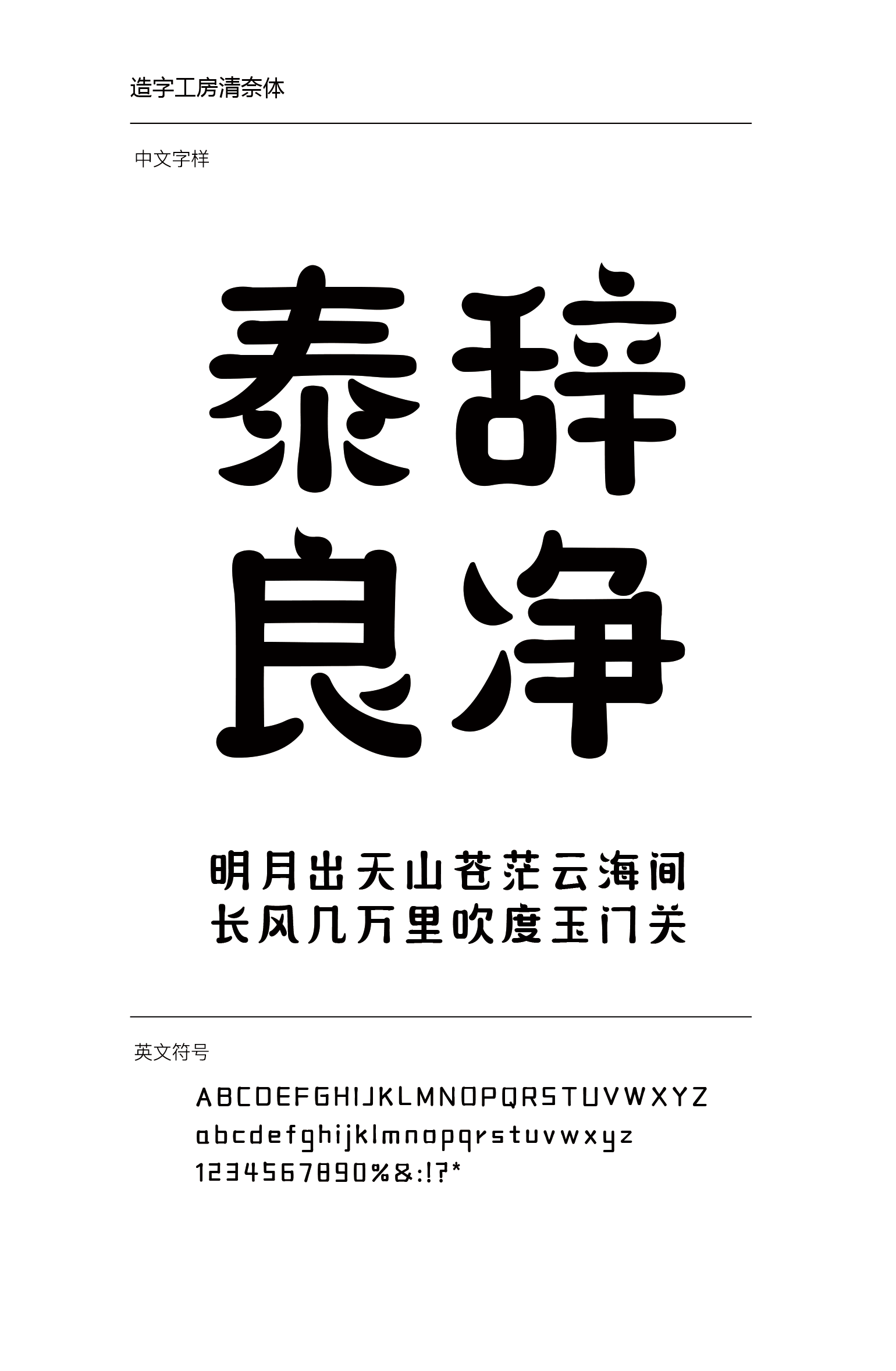
造字工房清奈体设计说明 造字工房清奈体,其字形方润丰腴,笔意舒展充畅,宛转流美,神气充足。横折圆转含蓄,味韵雅致,稳健端庄,沉厚而不凝滞、酣畅而不佻薄,给人以柔美灵动之感,婉转畅达,有极强的视觉表现力。适用于大标题及个性品牌设计推广等环境。本字体为简体字库,采用OpenType/CID格式,Adobe-GB1-5编码。基于中华人民共和国GB2312-80字符集标准,另按需添加101个汉字。共收容字数6864CJK汉字,ASCII常用字符100个。 造字工房清奈体下载地址 点击下载